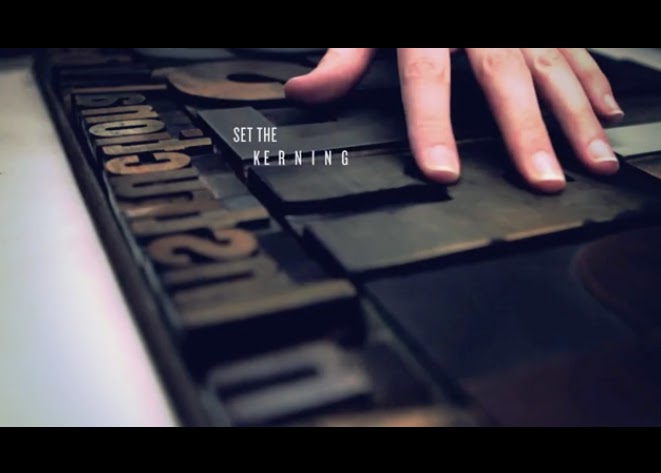
En innumerables ocasiones hemos escuchado hablar de que algo ha sido impreso en Letterpress, incluso en Lettering Time hemos compartido entradas como "Las mejores Tarjetas en Letterpress" o "Impresión de tipos móviles".
Pero..
¿Qué es el letterpress?
El letterpress es un una técnica que permite imprimir mediante la aplicación de presión sobre la superficie que se desea imprimir, dejando su huella y textura grabadas. Este proceso de impresión puede llevarse a cabo con o sin tinta alguna. El "letterpress" es la denominación inglesa que en español se le suele traducir como impresión tipográfica.
Me gusta mucho la definición, algo poética, que tiene los amigos argentinos de Mil Letterpress Boutique Tipográfica en su web:
"... Una imagen que podés sentir, tocar, percibir el relieve, la forma, la profundidad... Un papel grueso, con relieve, trama, con humedad y olor a algodón... Tinta rica, espesa y orgánica... Si Letterpress fuera comida sería como el chocolate... Aterciopelado..."
¿Cuando surge el Letterpress?
La técnica de letterpress es algo que se lleva realizando desde mediados del siglo pasado ya que la historia del letterpress se remonta hacia 1440, año en el que se le atribuye a Johannes Gutenberg la invención de la imprenta de tipos móviles en occidente, puesto que hay constancia que en oriente ya se trabajaba con esta técnica de impresión en el año 1040 D.C.
Puedes conocer mas sobre la historia de la impresión en letterpress aquí. Por supuesto que también os recomiendo el libro escrito por Paco Vela, "Typographica, la historia del arte de imprimir", para conocer a fondo, y de buena mano, los orígenes de la imprenta.
¿Como hacer letterpress?
La técnica del letterpress tradicional consiste en preparar el diseño con moldes de letras o ornamentos, generalmente realizados en madera o plomo, los cuales se entintan para luego mediante presión imprimir el diseño creado en el papel sin ningún paso intermedio. Al no producirse un reparto uniforme de la tinta por todo el diseño, se crean pequeñas imperfecciones al poner en contacto el molde y el papel. Estas imperfecciones dan personalidad a este tipo de impresión y son amadas por los seguidores del letterpress.
Además de quedarse la tinta impregnada en el papel, se crean unas pequeñas profundidades en el lugar donde contacta el molde. Si el papel es lo suficientemente grueso y de textura algodonosa se consigue un efecto de bajo relieve añadiendo mayor textura al resultado final. Como ya hemos comentado anteriormente, este proceso se puede realizar con o sin aplicar tinta, conociéndose este ultimo caso con el nombre de golpe en seco o gofrado y podemos verlo explicado a la perfección en este video de Omán Impresores.
En la actualidad este metodo de impresion ya no se limita solo a los tipos móviles existentes, sino que mediante la utilización de programas de edicion vectorial, podemos imprimir en letterpress cualquier diseño que podamos realizar en nuestro ordenador. Estos diseños se trasladan a una placa de zinc fotograbada conocida dentro del gremio como "Cliché".
Puedes conocer mas sobre el proceso y las herramientas que se utilizan para la impresión tradiconal en este articulo del blog de Lola Espinosa y en los siguientes videos:
¿Cuales son los papeles adecuados para Letterpress?
Podemos encontrar muchísimas marcas que fabrican papeles adecuados para realizar impresión letterpress en el mercado, pero elijamos el que elijamos debemos tener en cuenta que cumpla ciertas características:
⇛ Debe ser un papel de alto contenido en fibras de algodón, a poder ser 100% algodón, ya que al ejercer mucha presión en este tipo de impresión, la fibra del papel debe poder soportar dicha presión sin que se agriete o rompa.
⇛ Debe tener un gramaje (espesor) considerable ya que, como ya hemos comentado, con este tipo de impresión se obtienen bajorrelieves (hundimiento en en el papel) o relieves (conocidos técnicamente como gofrados). No es recomendable utilizar un papel de menos de 300 gramos. Los gramajes mas usados para la impresión en Letterpress suelen ser entre 350 y 400 gramos, aunque podemos encontrar papeles de hasta 600 gramos con cierta facilidad.
Hay muchas marcas de papel que fabrican papeles de alto gramaje adecuados para letterpress, como el Canaletto de Neenah Paper que sale en 600 gramos, Cordenons Wild que llega hasta unos maravillosos 850 gramos, o los papeles Century Cotton Wove con hasta 350 gramos o Arcodesign con un máximo de 580 gramos, ambos dos de Fedrigoni.
El papel que solemos ver en la mayoría de imágenes que encontramos en pinterest, Instagram, etc, con preciosos trabajos realizados en Letterpress, suele ser el Crane Lettra de 600 gramos, el cual fue creado expresamente para trabajos de letterpress por la empresa americana Crane. Este papel ha sido difícil de encontrar fuera de Estados Unidos, además su precio suele ser elevado, pero cada vez mas imprentas tradicionales fuera de EEUU lo están incorporando a sus catálogos de papel.
☙ Jukebox. Todo un referente mundial de la impresión en letterpress.